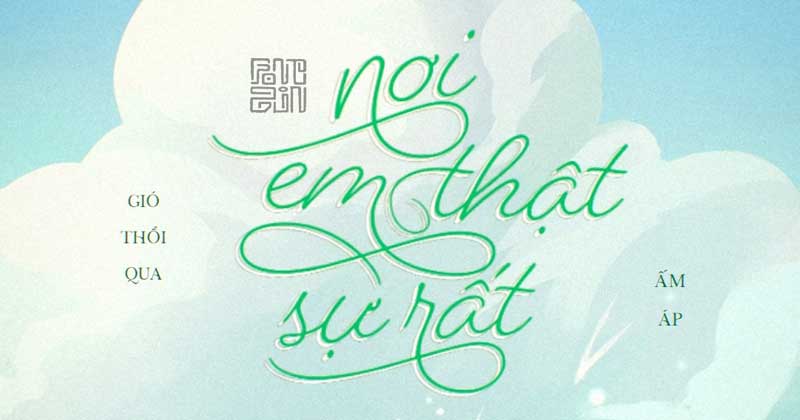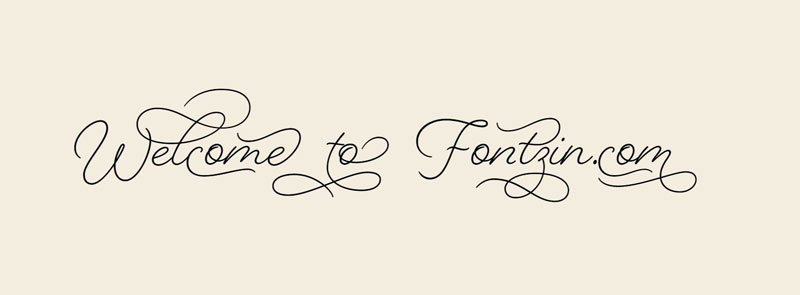
Font Việt hóa viết tay Beloved hơn 3000 glyph
Giới thiệu Font Việt hóa viết tay Beloved Script
Một nội dung content hình ảnh thì nhất thiết phải có 1 vài bộ Font Việt hóa viết tay xịn đúng không các bạn. Chính vì lý do này nên Team FontZin đã Việt hóa bộ font Beloved bom tấn này nhân ngày 20.10 để chia sẻ đến các bạn.
Font Việt hóa viết tay Beloved hơn 3000 glyph
Font Việt hóa viết tay Beloved Script
Bộ Font Việt hóa Beloved Script được thực hiện bởi FontZin. Font này được thiết kế bởi Laura Worthington và được tích hợp vào tài khoản Adobe, chính điều này lại thêm một phần chắc chắn về sự chuẩn chỉnh của font.
Beloved Script là Font chữ mô phong chữ viết tay bằng bút bi. Với các nét vẽ đơn giản mono-line đã tạo nên một bộ font có sự đồng điệu uyển chuyển mà dễ nhìn giống như chúng ta cầm bút viết nên vậy.
Font Beloved Script Việt hóa viết tay với 3000 ký tự mở rộng
Font Việt hóa viết tay Beloved hơn 3000 glyph
Font Beloved Script Việt hóa
Beloved Script tuy là một bộ font có nhiều ký tự thay thế nhưng khi thiết kế ra một sản phẩm lại có hiệu ứng thị giá rất tốt. Với hơn 3000 ký tự thay thế để lựa chọn, bao gồm chữ viết hoa, chữ thường, các nét uốn lượn bạn có thể tạo ra một tác phẩm tuyệt vời.
• Font được Việt hóa hoàn chỉnh ký tự cơ bản và glyph thay thế.
• Font tối ưu hóa feature cho tiếng Việt và tích hợp mã unicode UPA